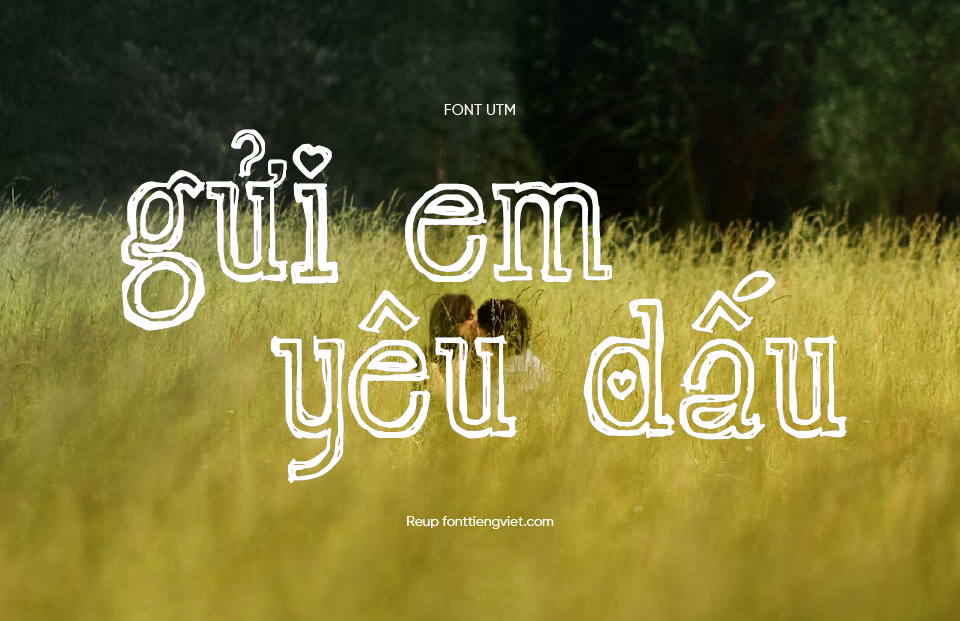
Font Việt hóa UTM Chickenhawk
Font Việt hóa UTM Chickenhawk – Bộ Font Chữ Nghệ Thuật Độc Đáo Cho Thiết Kế
Giới thiệu về Font Việt hóa UTM Chickenhawk
Trong thế giới đồ họa hiện đại, việc tìm kiếm một bộ Font Miễn Phí chất lượng luôn là ưu tiên hàng đầu của các nhà thiết kế. Font Việt hóa UTM Chickenhawk nổi lên như một lựa chọn hoàn hảo nhờ phong cách phóng khoáng và đường nét sắc sảo. Đây là bộ phông chữ thuộc gia đình UTM nổi tiếng, được tinh chỉnh tỉ mỉ để phù hợp hoàn toàn với bảng mã Unicode của tiếng Việt. Điều này giúp người dùng không còn lo lắng về lỗi gõ dấu khi sáng tạo trên các phần mềm như Photoshop hay Illustrator. Với cấu trúc ký tự mang hơi hướng retro kết hợp hiện đại, bộ font này mang lại cảm giác mạnh mẽ nhưng vẫn rất mềm mại và uyển chuyển cho mọi tác phẩm nghệ thuật.
Đặc điểm nổi bật của Font Việt hóa UTM Chickenhawk
Thiết kế ấn tượng và đa dụng
Font Việt hóa UTM Chickenhawk sở hữu những nét vẽ đậm chất cá tính, phù hợp cho các dự án yêu cầu sự phá cách. Các chữ cái được thiết kế với độ tương phản tốt, giúp thông điệp trở nên nổi bật và dễ đọc hơn. Đối với các bạn học sinh và sinh viên, đây là công cụ đắc lực để trang trí bìa báo tường, làm slide thuyết trình hay thiết kế thiệp mời. Sự cân bằng giữa các khoảng cách ký tự giúp văn bản trông chuyên nghiệp và bắt mắt ngay từ cái nhìn đầu tiên.
Ứng dụng thực tế trong giáo dục và đời sống
Không chỉ dừng lại ở thiết kế chuyên nghiệp, phông chữ này còn được ứng dụng rộng rãi trong trường học. Giáo viên có thể dùng nó để tạo ra các tiêu đề bài giảng sinh động, kích thích sự hứng thú của học sinh. Nhờ tính năng việt hóa chuẩn, việc soạn thảo các đoạn trích dẫn hay châm ngôn ý nghĩa trở nên nhanh chóng và hiệu quả hơn bao giờ hết.